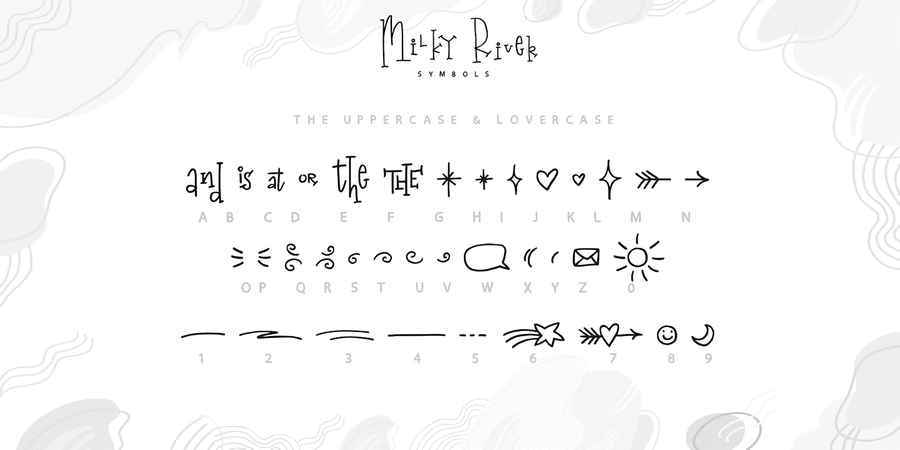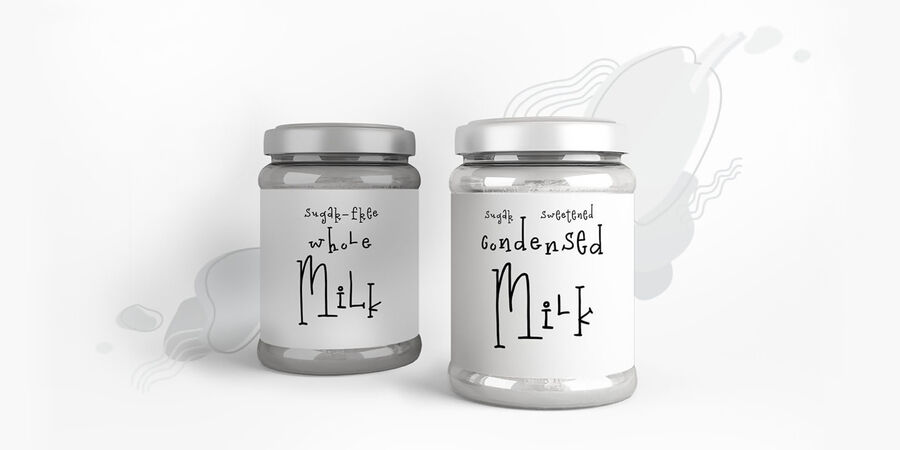
Опис гарнітури Milky River CyrillicMilky River грайливий дитячий шрифт + додатковий декоративний шрифт.
Це намальований вручну шрифт, який підходить для брендингу, логотипів, соціальних мереж, етикеток, дизайну упаковки і заголовків блогів.
Шрифт Milky River містить повний набір великих і малих літер і 26 лігатури подвійних букв а також цифри і знаки.
Багатомовна підтримка для 32 мов: латинські гліфи для африкаанс, албанська, баскська, боснійський, каталанська, датська, голландська, англійська, естонська, фарерська, філіппінська, французька, галісійська, індонезійська, ірландська, італійська, малайська, норвезька букмол, португальська, Словенська, іспанська, суахілі, шведська, турецька, валлійська, зулуська.
І підтримка кирилиці російською, українською, білоруською, болгарською та казахською мовами.
Шрифт розробила Ірина Двілюк у 2021 році.
Асоціації з сімейством шрифтів Milky River CyrillicОсобистість і характер гарнітури:
наївний, рукотворний, грайливий, потішний, прикольний, характерний, крафтовий, кустарний, саморобний, органічний, артізанальний, дивний, божевільний, химерний, вернакулярний, смішний, неформальний, легковажний, карикатурний, мультяшний, домашній, ручний, високий, оригінальний, живий, дитячий, святковий, веселий, жартівливий, стрибучий, хуліганський, комічний, дотепний, літній, артистичний, динамічний, емоційний, лихий, рухливий, непосидючий, яскравий, милий, доброзичливий, зелений, привітний, радісний, пустотливий, весняний, щасливий, танцюючий, моторний, вільний, сміливий, цікавий, енергійний, самобутній, мрійливий, виразний, творчий, активний, симпатичний, позитивний, музичний, мотузковий, неслухняний, вольний, задерикуватий, темпераментний, легкий, тонкий, крихкий, колоритний, нервовий, дівчачий, казковий, чарівний, інтимний, красивий, гарненький, свіжий, повітряний, натхненний, ліричний, чуттєвий, романтичний, ритмічний, епістолярний, ніжний
іграшка, гра, анімація, розваги, геловін, мультфільм, квест, дитяча книжка, канікули, кафе, хенд мейд, графіка, ілюстрація, дім, тату, татуювання, свято, гумор, табір, цирк, відпочинок, школа, щоденник, зошит, Інстаграм, ранок, весна, подарунки, селфі, театр, туризм, канцтовари, олівці, фломастери, пластилін, пригоди, учень, школяр, принцеса, казка, магія, солодощі, десерт, кондитер, АСМР, Хюґе, сувенір, романтика, світанок, школярка, фея Гарнітура асоціюється з віком: